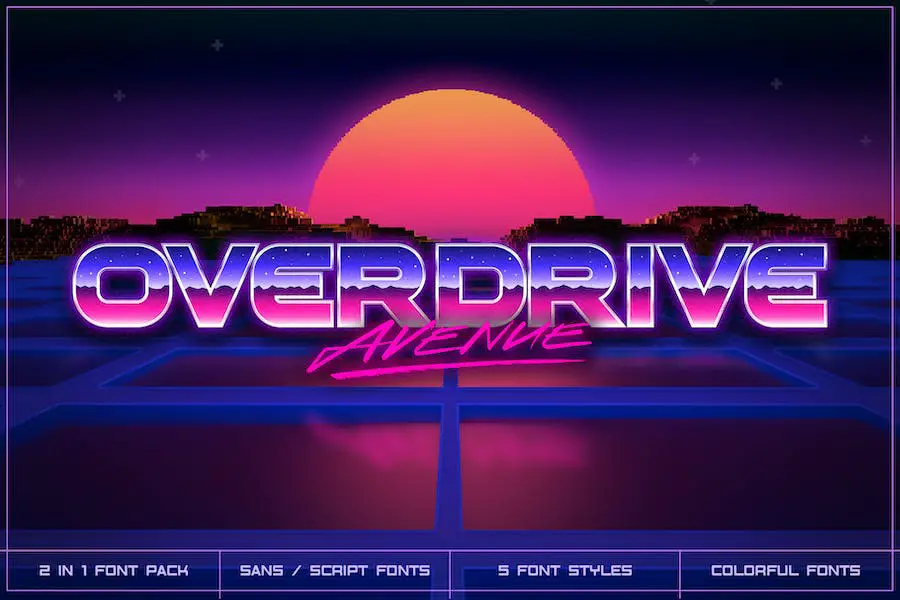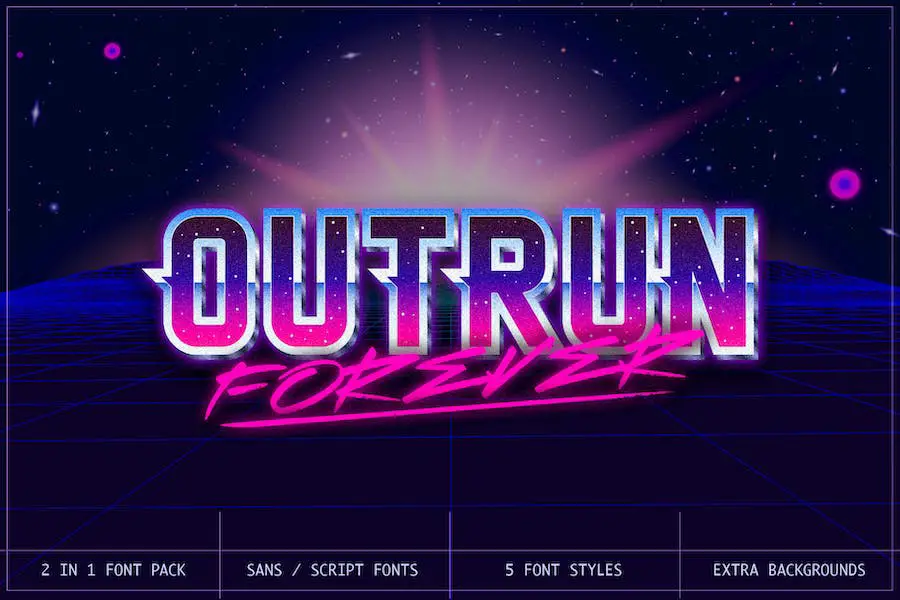
2023년 최고의 VHS 글꼴 15개(무료 및 프리미엄)
게시 됨: 2023-09-23프로젝트를 한 단계 더 발전시킬 수 있는 완벽한 글꼴을 찾고 있는 그래픽 디자이너이신가요? 글쎄, 더 이상 보지 마세요! 이 기사에서는 디자인을 향상시키고 복고풍 느낌을 주는 데 도움이 되는 최고의 VHS 글꼴에 대해 논의할 것입니다.
하지만 목록을 살펴보기 전에 VHS 글꼴을 특별하게 만드는 이유와 사용을 고려해야 하는 이유에 대해 여러분이 가질 수 있는 일반적인 우려 사항을 해결해 보겠습니다.
"VHS"라는 용어는 거친 비디오, 향수를 불러일으키는 영화의 밤, 80년대와 90년대의 상징적인 모습에 대한 추억을 불러일으킬 수 있습니다. VHS 글꼴은 빈티지한 미학을 캡슐화하여 디자인에 향수와 진정성을 부여합니다.
대담하고 각도가 있으며 종종 오래된 VHS 테이프의 불완전성을 모방하는 결함 있는 요소가 특징입니다. VHS 글꼴을 프로젝트에 통합하면 청중을 즉시 과거로 데려가 그 시대와 관련된 감정을 불러일으킬 수 있습니다.
이제 이 기사에 대한 몇 가지 통계와 사실을 간단히 살펴보겠습니다. 우리는 현재 디자인 세계에서 유행하고 있는 최고의 VHS 글꼴을 직접 선택했습니다. 각 글꼴은 인기도, 다양성, 디자인 향상 능력을 기준으로 신중하게 선택되었습니다.
전단지, 포스터, 로고 또는 기타 유형의 그래픽 작업을 하든 이러한 글꼴을 사용하면 작업이 돋보일 것입니다.
이제 더 이상 고민하지 말고 바로 VHS 글꼴의 세계를 탐험해 보도록 하겠습니다. 다음 섹션에서는 최고의 추천 제품을 소개하고 이를 효과적으로 사용할 수 있는 방법의 예를 제공합니다.
디자인에 복고풍 감각을 추가하고 VHS 글꼴의 힘으로 청중을 사로잡을 준비를 하십시오!
최고의 프리미엄 VHS 글꼴
프로젝트에 향수와 복고풍 분위기를 더하고 싶으십니까? 우리가 엄선한 최고의 프리미엄 VHS 글꼴을 살펴보세요. 디자인을 한 단계 더 발전시키려면 필수 글꼴을 확인하세요.
블록레터
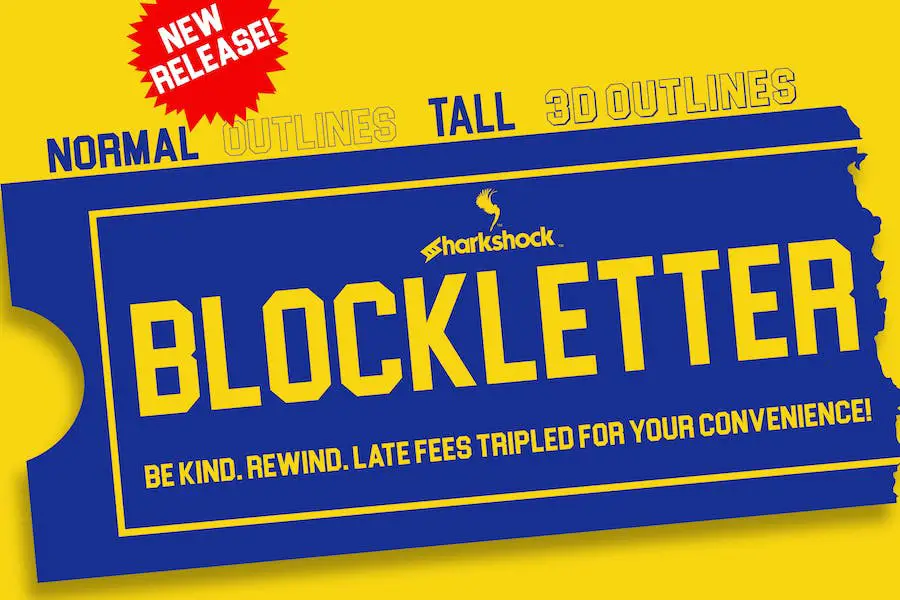
Blockletter는 상징적인 Blockbuster Video 로고에서 영감을 얻은 깔끔하고 기본적인 산세리프 글꼴입니다. 그래픽 디자인 프로젝트에 향수를 더하기에 완벽한 간단하고 간단한 디자인을 제공합니다.
깔끔한 라인과 클래식한 외관을 갖춘 Blockletter는 어떤 디자인에도 단순함과 강인함을 선사합니다. 복고풍에서 영감을 받은 포스터 작업을 하든, 빈티지 테마의 로고를 만들든 이 글꼴은 프로젝트를 향상시키고 진정성을 더해 줄 것입니다.
Blockletter 글꼴은 다목적이며 다양한 응용 프로그램에서 사용할 수 있습니다. 헤드라인과 본문 텍스트 모두에 적합하므로 응집력 있고 시각적으로 매력적인 디자인을 만들 수 있습니다.
또한 단순성 덕분에 읽기가 쉬워 메시지가 청중에게 효과적으로 전달될 수 있습니다.
비디오 카세트
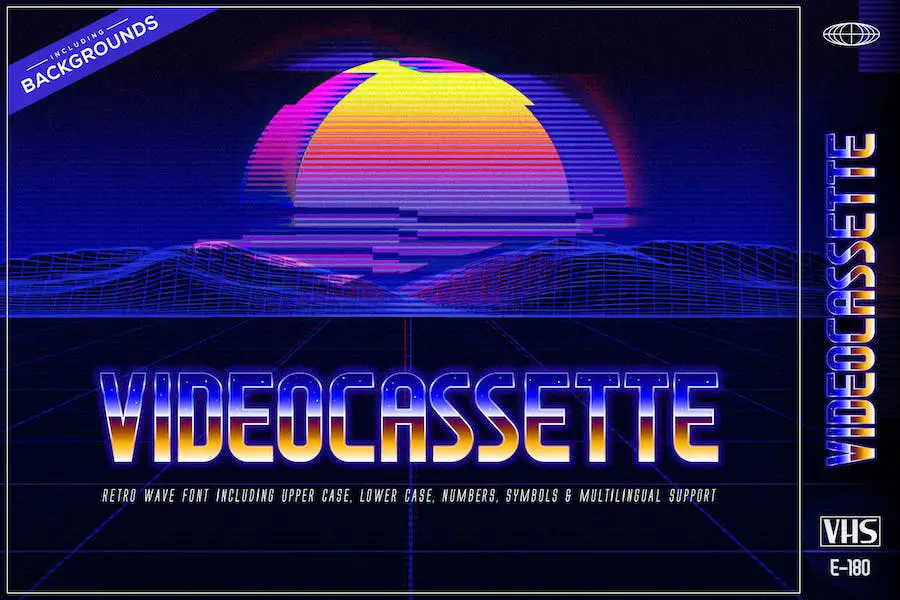
Videocassette는 디자인 프로젝트를 완전히 새로운 수준으로 끌어올릴 수 있는 놀라운 글꼴입니다. 80년대 VHS 시대의 복고풍 느낌을 완벽하게 포착하여 디자인에 향수와 빈티지한 느낌을 더해줍니다.
대담하고 두툼한 글자로 구성된 Videocassette는 눈길을 끄는 헤드라인, 제목 및 로고를 만드는 데 적합합니다. 포스터, 웹사이트, 포장 디자인 등 어떤 작업을 하든 이 글꼴은 귀하의 프로젝트를 돋보이게 만들어 줄 것입니다.
비디오카세트를 특별하게 만드는 것은 정통 레트로 웨이브 스타일입니다. VHS 시절의 추억을 되살려 디자인에 독특한 매력을 더해줍니다.
두껍고 약간 왜곡된 글꼴과 생동감 넘치는 색상이 결합되어 네온 불빛, 아케이드 게임 및 신스 음악의 시대로 즉시 돌아갑니다.
비디오카세트의 뛰어난 특징 중 하나는 다양성입니다. 다양한 디자인 스타일과 잘 어울리며 다양한 프로젝트에 사용할 수 있습니다. 대담하고 엣지있는 룩을 원하든, 더 부드럽고 유쾌한 분위기를 원하든 이 글꼴이 도움이 됩니다.
다양한 문자와 합자를 통해 무한한 창의적 가능성이 가능하므로 자유롭게 실험하고 자신만의 디자인을 만들 수 있습니다.
신호 없음
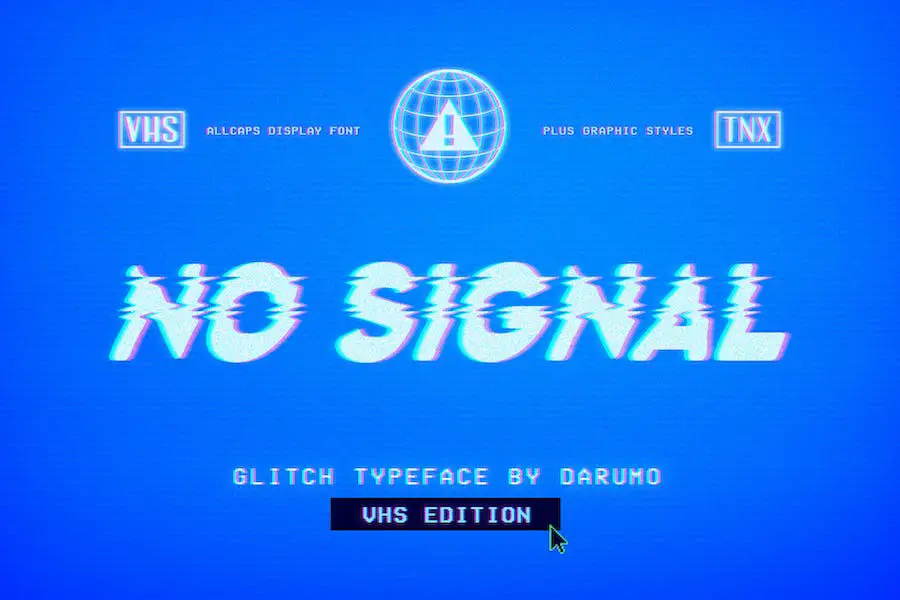
No Signal은 영화 포스터나 TV 프로그램과 같은 80년대 문화 제품에서 영감을 얻은 글리치 효과가 있는 디스플레이 글꼴입니다. 디자인에 눈길을 끄는 헤더와 텍스트 블록을 만드는 데 이상적입니다. 복고풍 미학을 갖춘 이 글꼴은 프로젝트에 향수를 불러일으키는 느낌을 선사합니다.
신호 없음의 글리치 효과는 디자인에 독특함과 향수를 더해 독특하고 기억에 남는 모습을 선사합니다.
영화 포스터 작업을 하든 TV 프로그램 그래픽을 만들든 이 글꼴은 80년대의 본질을 포착하고 눈에 띄는 디자인을 만드는 데 도움이 됩니다.
No Signal의 뛰어난 특성 중 하나는 다양성입니다. 대담하고 시선을 사로잡는 헤더 글꼴과 잘 어울리며, 보는 사람의 관심을 즉시 디자인으로 끌어들입니다.
하지만 텍스트 글꼴로도 빛을 발하여 모든 텍스트 블록에 개성과 감각을 더해줍니다. 소셜 미디어 그래픽부터 웹사이트 배너까지 다양한 디자인 프로젝트에 사용할 수 있으며 언제나 환상적으로 보일 것입니다.
목성 미션
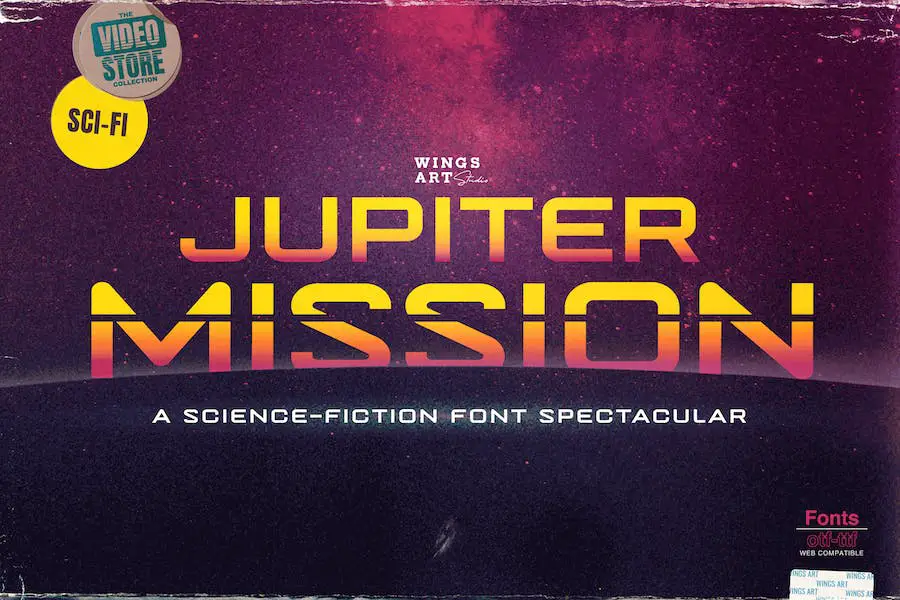
Jupiter Mission은 SF 영화와 TV 프로그램에서 영감을 얻은 미래 지향적인 글꼴 모음입니다. 매끄럽고 현대적인 디자인을 갖춘 이 글꼴은 그래픽 디자인 프로젝트에 미래 지향적인 느낌을 더하는 데 적합합니다.
Jupiter Mission 글꼴 제품군은 모든 그래픽 디자이너에게 꼭 필요한 다양한 속성을 자랑합니다. 깨끗하고 산뜻한 선은 텍스트에 미래지향적이고 첨단 기술을 더해 시선을 사로잡는 제목과 제목을 만드는 데 이상적입니다.
대담하고 기하학적인 모양은 각 캐릭터를 돋보이게 하여 디자인에 최대한의 영향을 줍니다.
Jupiter Mission은 미래 지향적인 미학을 제공할 뿐만 아니라 다양성도 제공합니다. 글꼴 모음에는 다양한 두께와 스타일이 포함되어 있어 다양한 모양을 실험하고 시각적으로 역동적인 구성을 만들 수 있습니다.
공상과학 영화 포스터를 디자인하든 미래 지향적인 웹사이트를 디자인하든 Jupiter Mission이 도와드립니다.
라군 해변
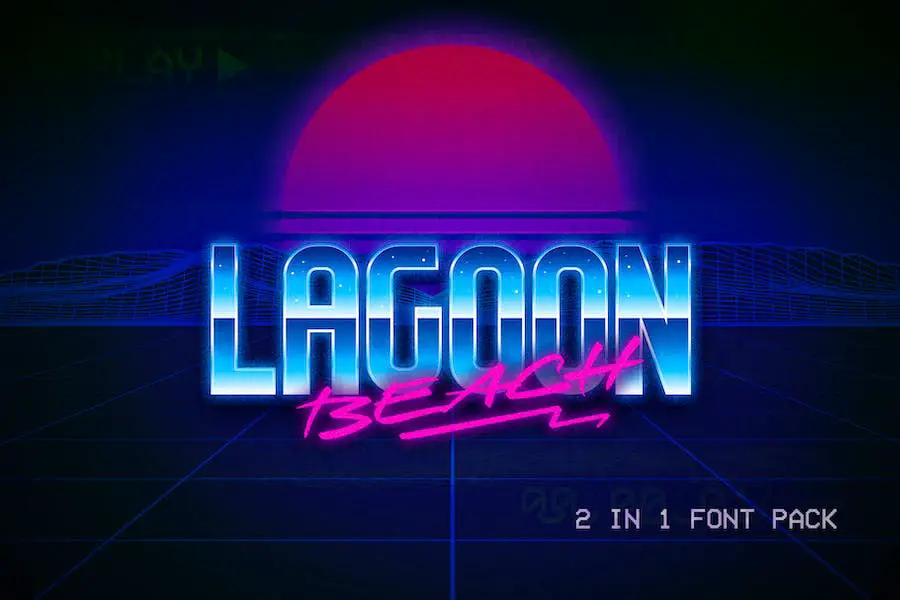
Lagoon Beach는 'It – 2 in 1 글꼴 팩'에 속하는 글꼴입니다. 이 글꼴 팩은 모든 프로젝트의 디자인을 향상시킬 수 있는 독특하고 다양한 글꼴 컬렉션을 제공합니다.
특히 라군 비치(Lagoon Beach)는 해변에서 영감을 받은 테마로 디자인에 휴식과 열대 분위기를 더해주는 능력이 돋보입니다.
Lagoon Beach를 사용하면 그래픽 디자인에 천국 같은 느낌을 더할 수 있습니다. 바다의 파도를 닮은 굵은 글씨체와 필기체 글씨체를 조합한 글꼴이 특징입니다. 여행, 해변 휴양지, 여름 이벤트 등과 관련된 프로젝트에 적합합니다.
라군 비치의 가장 큰 특징 중 하나는 다양성입니다. 이 글꼴은 제목, 로고, 포스터, 소셜 미디어 그래픽 등 다양한 방식으로 사용될 수 있습니다. 독특한 스타일은 확실히 청중의 관심을 끌고 작품의 전반적인 시각적 매력을 향상시킬 것입니다.
좀비 펑크
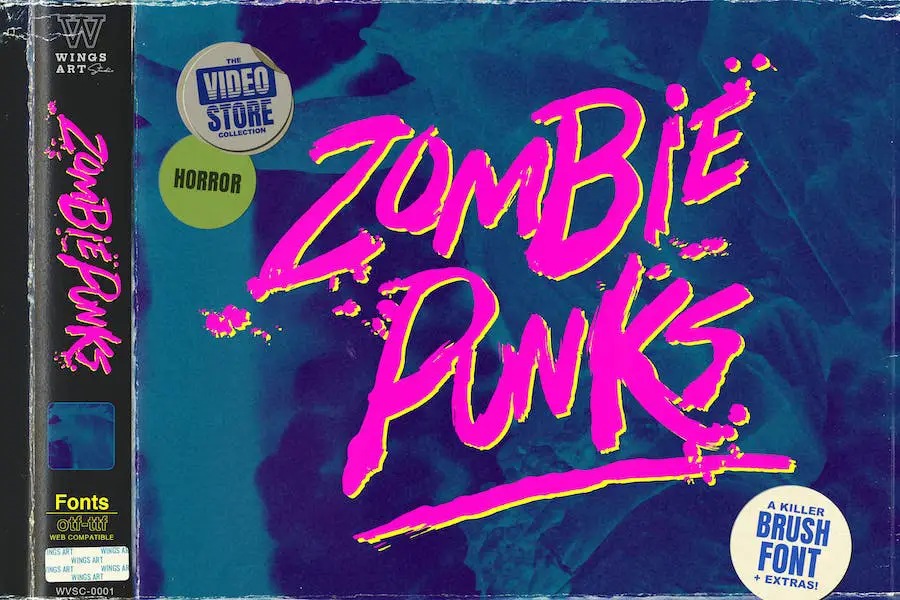
Zombie Punks는 디자인에 고전적인 공포 느낌을 더해주는 지저분한 손으로 그린 브러시 글꼴입니다. 이 다용도 글꼴은 두 가지 스타일로 제공되며 밑줄과 페인트 유출도 추가되어 진정성을 더해줍니다.
거칠고 생생한 미학으로 Zombie Punks는 80년대 VHS 글꼴의 본질을 포착합니다. 낡고 고민스러운 모습은 귀하의 프로젝트를 비디오 카세트 테이프와 공포 영화의 황금 시대로 즉시 되돌려 놓을 것입니다.
복고풍 테마의 포스터, 앨범 표지, 웹사이트 헤더 등 어떤 작업을 하든 Zombie Punks는 디자인을 향상시킬 수 있는 완벽한 선택입니다. 손으로 직접 만든 문자는 일반 글꼴로는 얻을 수 없는 독특하고 개인적인 느낌을 작품에 부여합니다.
포함된 두 가지 스타일은 훨씬 더 다양한 기능을 제공합니다. 헤드라인과 제목에 딱 맞는 깔끔하고 읽기 쉬운 모양을 원하면 '일반' 스타일을 사용하세요. 좀 더 지저분하고 풍화된 외관을 원하면 '더티(Dirty)' 스타일로 전환하여 빈티지 정통성을 추가하는 데 이상적입니다.
깨진 콘솔
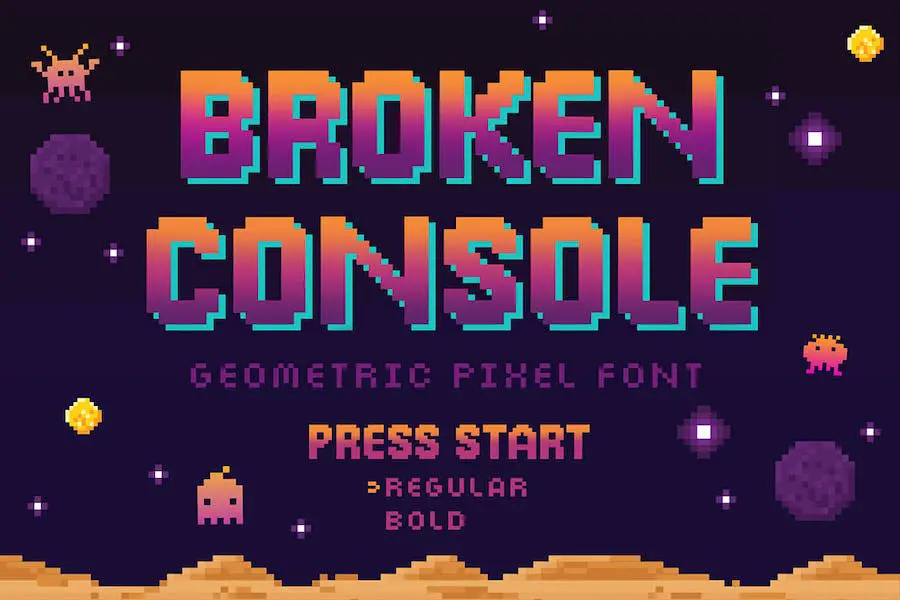
Broken Console은 구식 게임 콘솔에서 영감을 얻은 기하학적 픽셀 글꼴입니다. 픽셀화된 디자인으로 픽셀 아트의 향수를 불러일으키는 매력을 완벽하게 포착합니다. 이 글꼴은 일반(1픽셀), 볼드(2픽셀) 및 그림자의 세 가지 스타일로 제공됩니다.
레귤러 스타일은 디자인에 복고풍 향수를 더하는 데 적합합니다. 클래식 비디오 게임에서 흔히 볼 수 있는 픽셀 글꼴을 모방한 깨끗하고 미니멀한 모양이 특징입니다.
빈티지 테마 프로젝트를 진행 중이거나 단순히 디자인에 재미있는 요소를 추가하려는 경우 일반 스타일의 Broken Console이 적합합니다.
좀 더 대담한 표현을 원하는 사람들에게는 볼드 스타일이 더욱 뚜렷하고 눈길을 끄는 룩을 제공합니다. 이중 픽셀을 사용하는 이 스타일은 디자인에 강도를 한 단계 더 추가합니다.
헤드라인이나 관심을 끌고 대담한 영향을 주고 싶은 기타 영역에 이상적입니다.
도넛밴
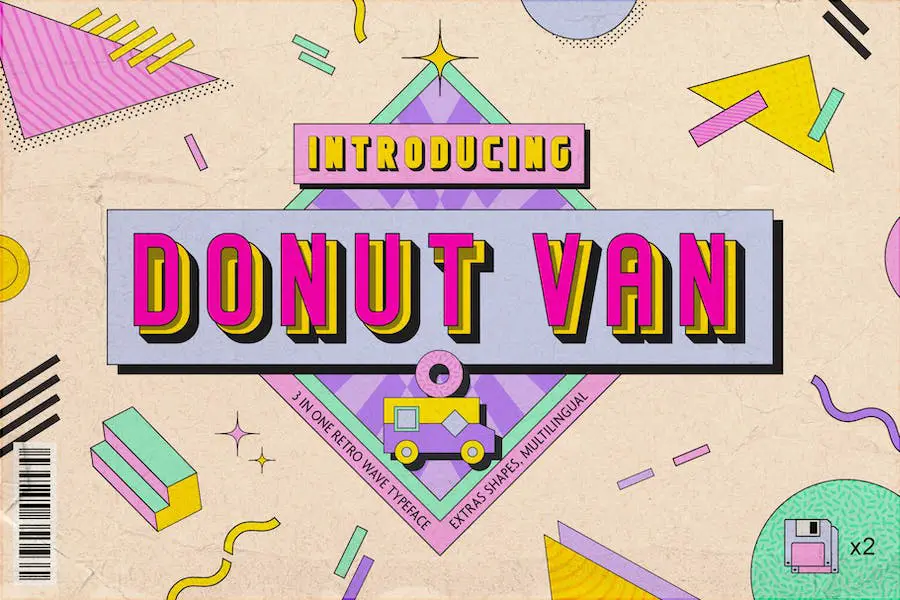
Donut Van은 프로젝트에 멤피스 트렌디한 디자인을 가미한 달콤한 복고풍 웨이브 스타일을 제공하는 다채로운 트리오(3 in 1) 글꼴 모음입니다. 하나의 패키지에 세 가지 변형을 제공하는 다용도 글꼴로, 디자인에 재미있고 생동감 넘치는 분위기를 더할 수 있습니다.
포스터, 로고 또는 기타 그래픽 디자인 프로젝트를 진행하든 Donut Van은 독특하고 눈길을 끄는 특성을 제공합니다.
Donut Van 글꼴 패밀리의 하이라이트 중 하나는 다채로운 성격입니다. 생생하고 대담한 색상 팔레트를 갖춘 이 글꼴은 모든 디자인에 즉각적인 밝기를 추가합니다.